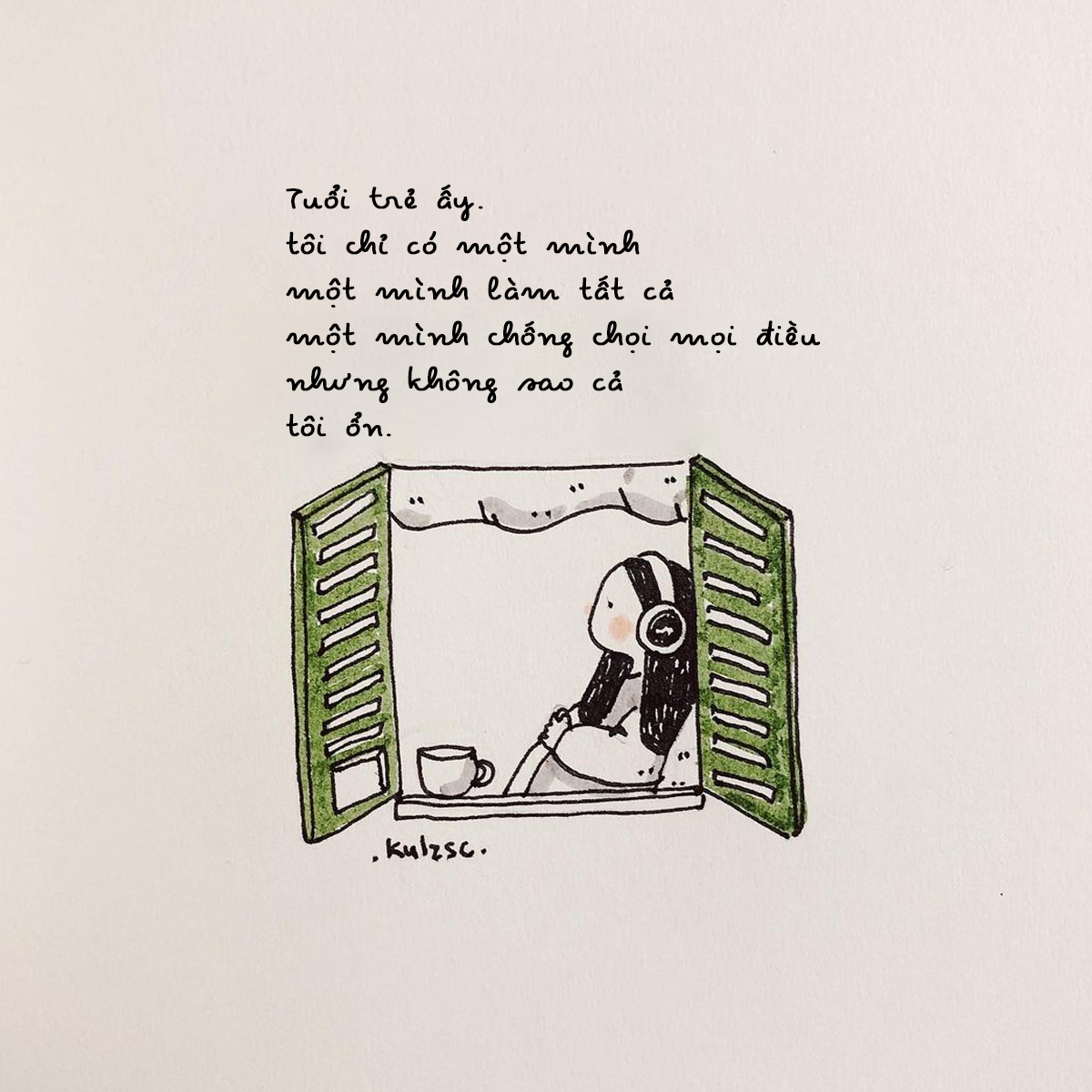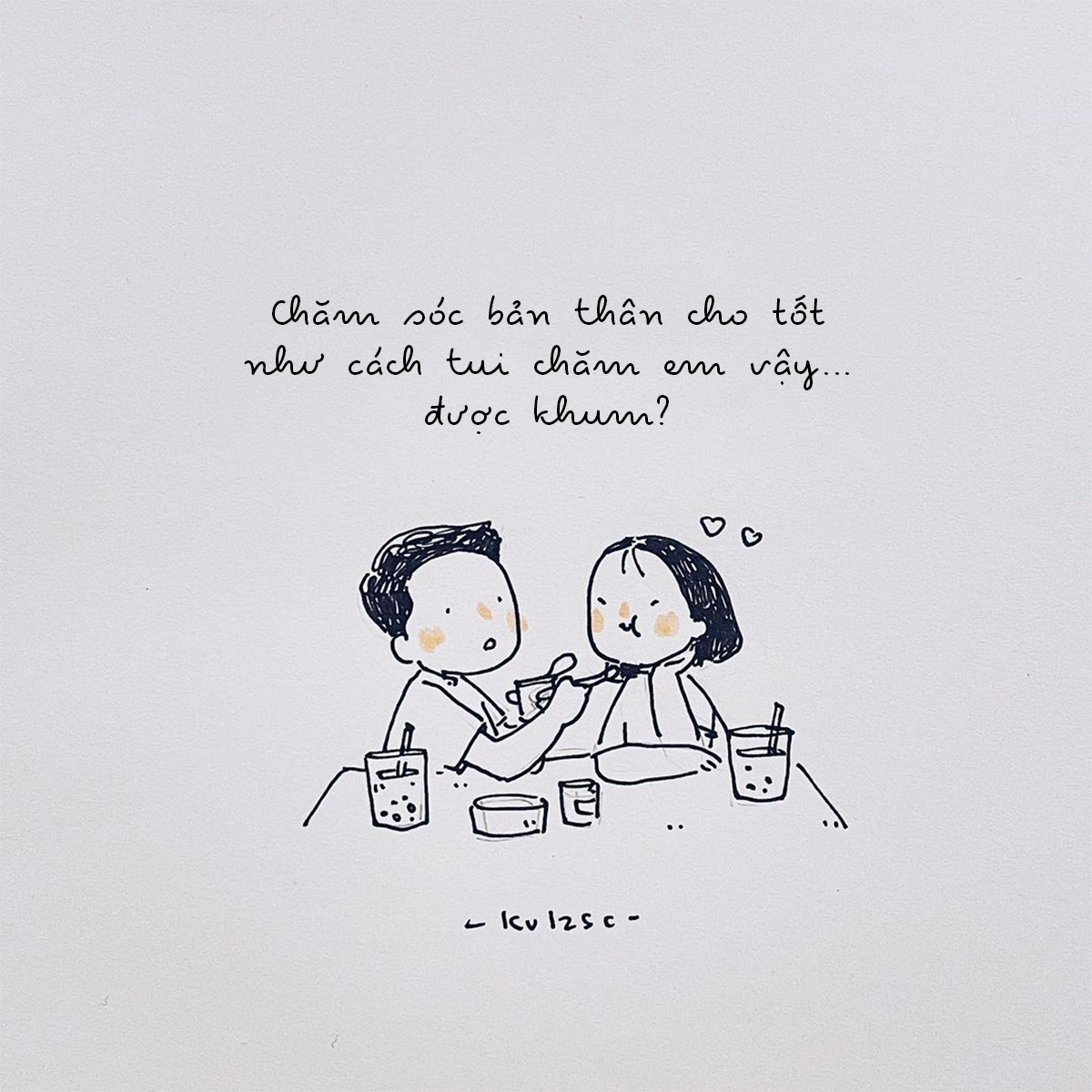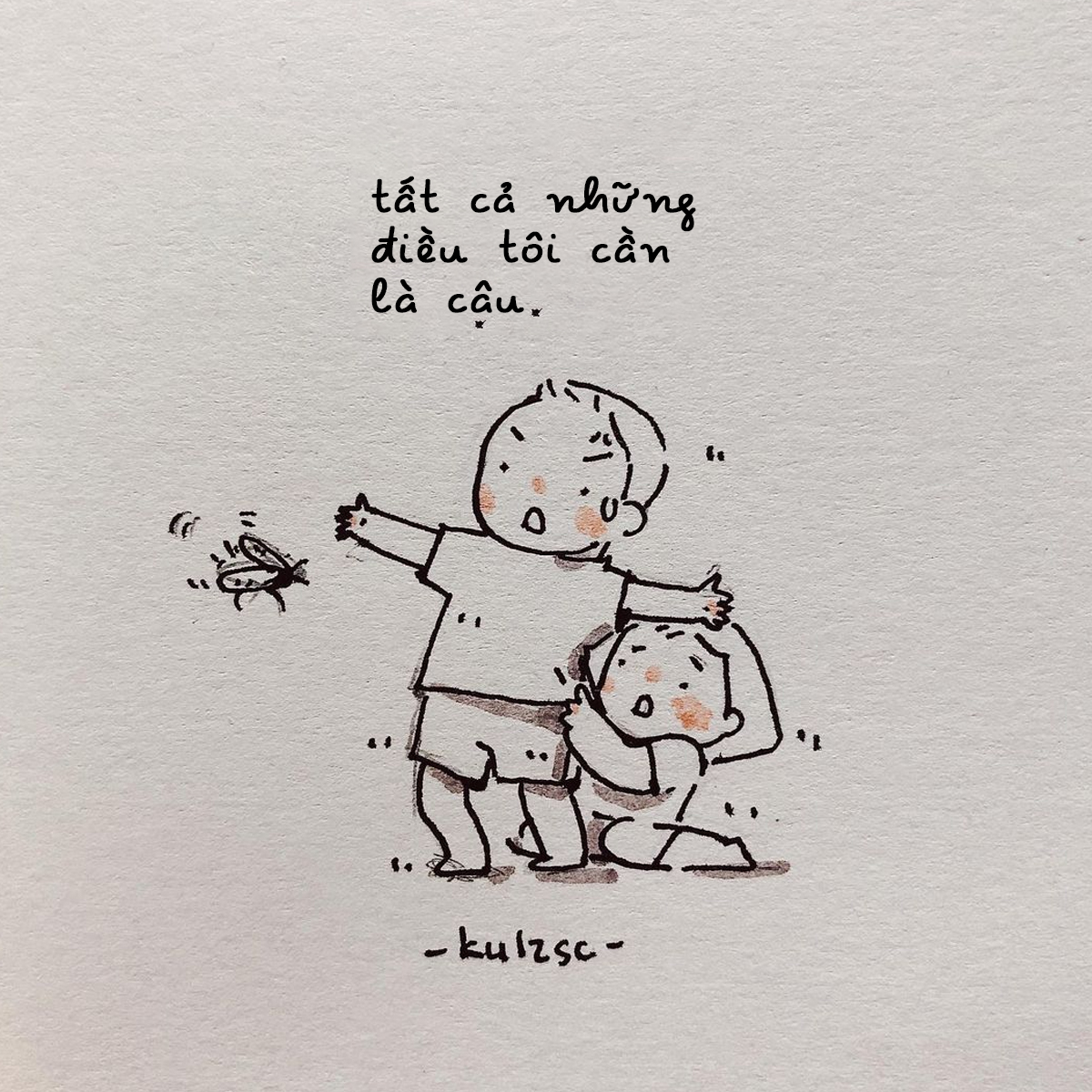
Font Pecita Việt Hóa – Font phù hợp thiết kế quotes
Pecita là một font chữ lấy cảm hứng từ chữ viết tay được thiết kế bởi Philippe Cochy một tác giả đến từ đất nước nổi tiếng với tháp Eiffel. Font chữ được mã hóa bằng Unicode với tất cả các ký tự chữ Latinh được sử dụng trong hầu như mọi ngôn ngữ.
Phông chữ này khá phù hợp với các thiết kế quotes, viết thư, nhật ký, lyric, typographic…